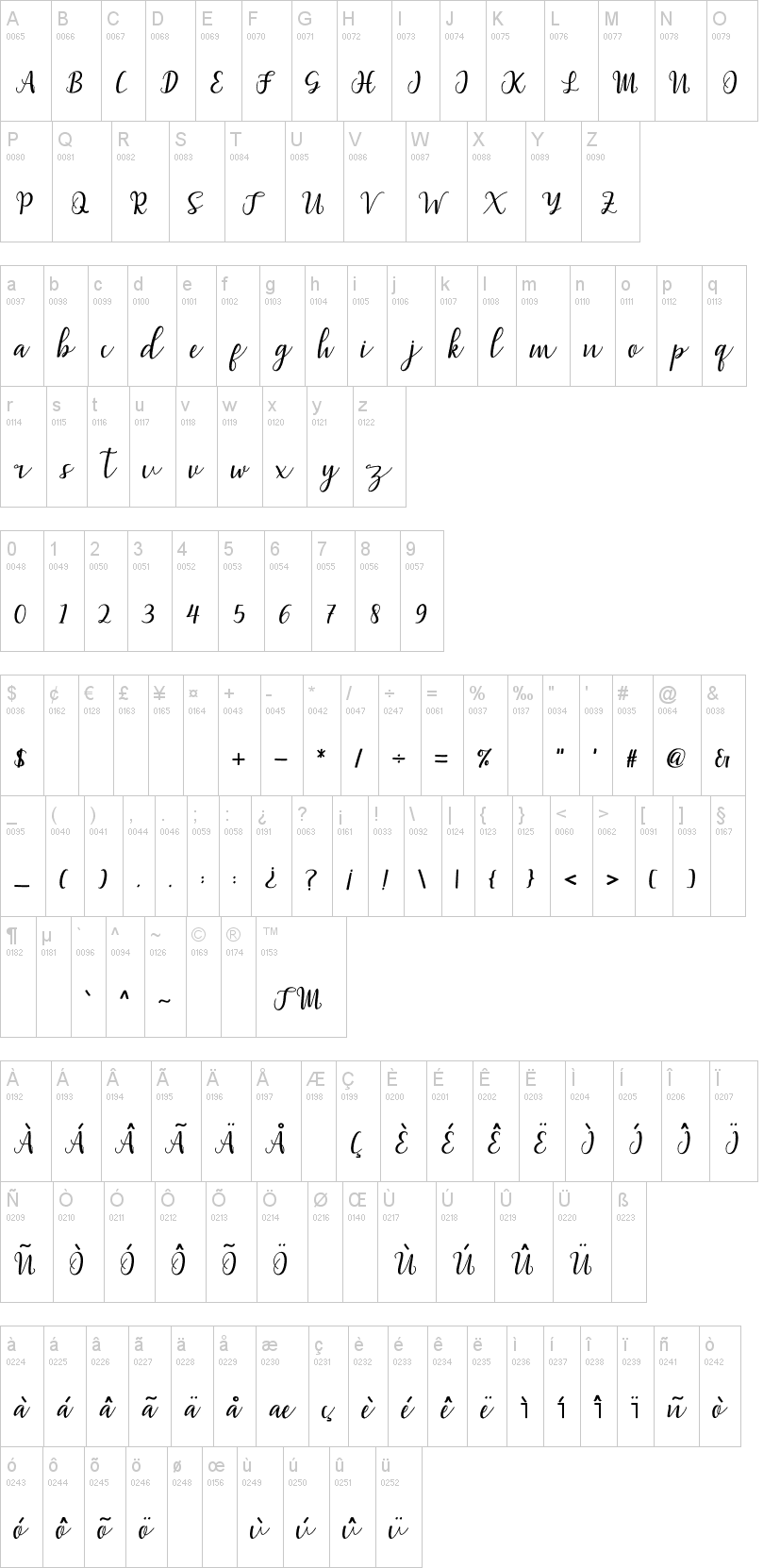
Millea Script 是一款流行的手写字体,由著名设计师Millea 所创作。它具有温柔、活泼、优雅的特点,能够很好的表达出文字的情感,是一款非常经典的字体。它的字体风格活泼、可爱,适用于各种类型的文档,尤其是用于文字装饰、插图、卡片等,能够带给读者更多的情感体验。内容介绍
Millea Script是一款非常不错的手写艺术字体,具有很好的视觉感,适合于文化类的宣传设计、商业类品牌的广告和产品包装设计以及个性化文字排版等较多场景。